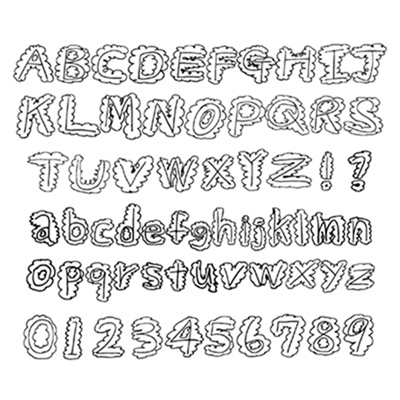
もくもくふぉんと
もくもく雲のよう。もくもくもくもく
Artist安田直樹
Designerさとうひろゆき
Organizationあそ美
もくもくふぉんとです。みなさん使ってください。(安田直樹)
NAOKIFONTにつづき以前から書いていた「もくもくふぉんと」がついにデビュー!雲のようにもくもくなんだか素敵です。(さとうひろゆき)
いつもは電車の絵や旅行先の絵を描いています。フォント(文字)へのチャレンジは始め自信がない様子でしたが、挑戦して2種類目になりました。今後も挑戦し続けて欲しいです。(あそ美)